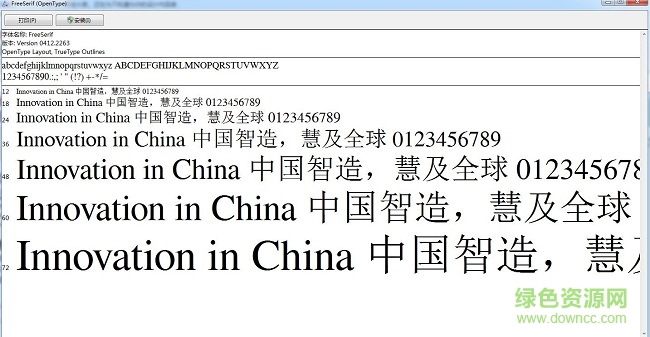
freeserif.ttf字體是一款同時(shí)支持中文和英文輸入的襯線(xiàn)字體,易讀性高,適用性強(qiáng),視覺(jué)效果良好,通常用在書(shū)籍、報(bào)紙、雜志等方面,需要的朋友快來(lái)綠色資源網(wǎng)下載吧!
筆畫(huà)橫平豎直,橫細(xì)豎粗,棱角分明,結(jié)構(gòu)嚴(yán)謹(jǐn),整齊均勻,有極強(qiáng)的筆畫(huà)規(guī)律性,從而使人在閱讀時(shí)有一種舒適醒目的感覺(jué)。
常用的serif(襯線(xiàn)字體)字體為T(mén)imes New Roman、Georgia、宋體